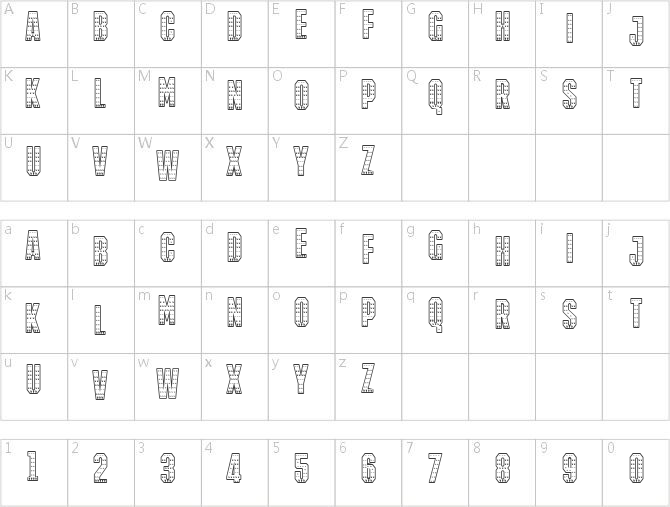
IRON MAN OF WAR 111A NCV
IRON MAN OF WAR 111A NCV介紹
IRON MAN OF WAR 111A NCV字體字庫是一款讓人賞心悅目、百看不厭的英文字體,適合各類廣告和產品包裝設計應用,字體大小0.6MB,格式為ttf字體,上傳用戶是順新廣告?,作者/版權方為未知